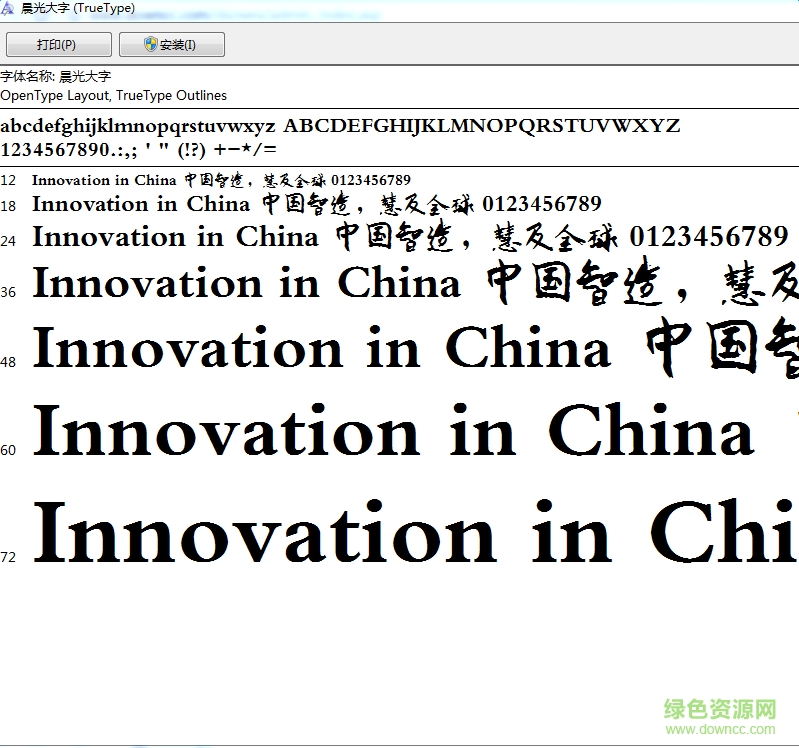
晨光大字简体是一款晨光类创意霸气风格字体软件,晨光大字体笔画随意却不失整体的工整性,粗细相间,非常的时尚,还有更多类似好看字体欢迎来绿色资源网下载体验!
晨光大字简体是一款应用于艺术设计方面的简体中文字体,该字体笔画粗壮,尾部的甩尾有力且有丰富的笔触细节,大字效果突出且引人注目;并且最大程度还原作者书写字形,细节表现完整,且字库完整,可以广泛应用于名片设计、新闻媒体、宣传海报、ppt、影视制作以及内容用字等领域。
该字体粗犷有力,尽显手写体洒脱气息,整体效果十分酷炫好看,尽显书法大师的魅力,用来耍酷再合适不过了!